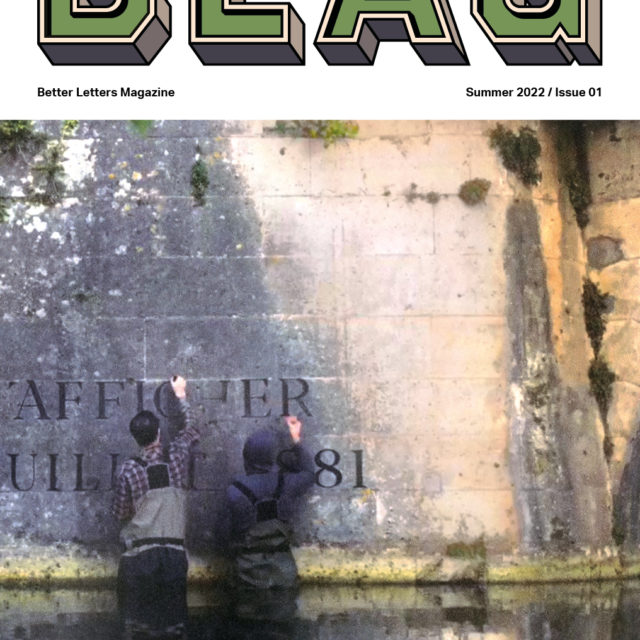
Reportaje de Santatipo en «Better Letters Magazine»
Un cartel con más de 100 años de historia, tiene su sitio en la nueva revista que ha lanzado Sam Roberts con Better Letters. Sam, también lleva las cuentas de Mr.Ghostsigns y es uno de los referentes en la rotulación pintada en paredes y fachadas.
En este primer número de la revista ha sacado el cartel de Holland American Line del Armador Francisco García. Un cartel del que podéis conocer su historia aquí y descargar una reproducción que hicimos en su momento.
Es un verdadero placer que parte del #PatrimonioGráfico de nuestra ciudad sea reconocido internacionalmente por su valor cultural y artístico.